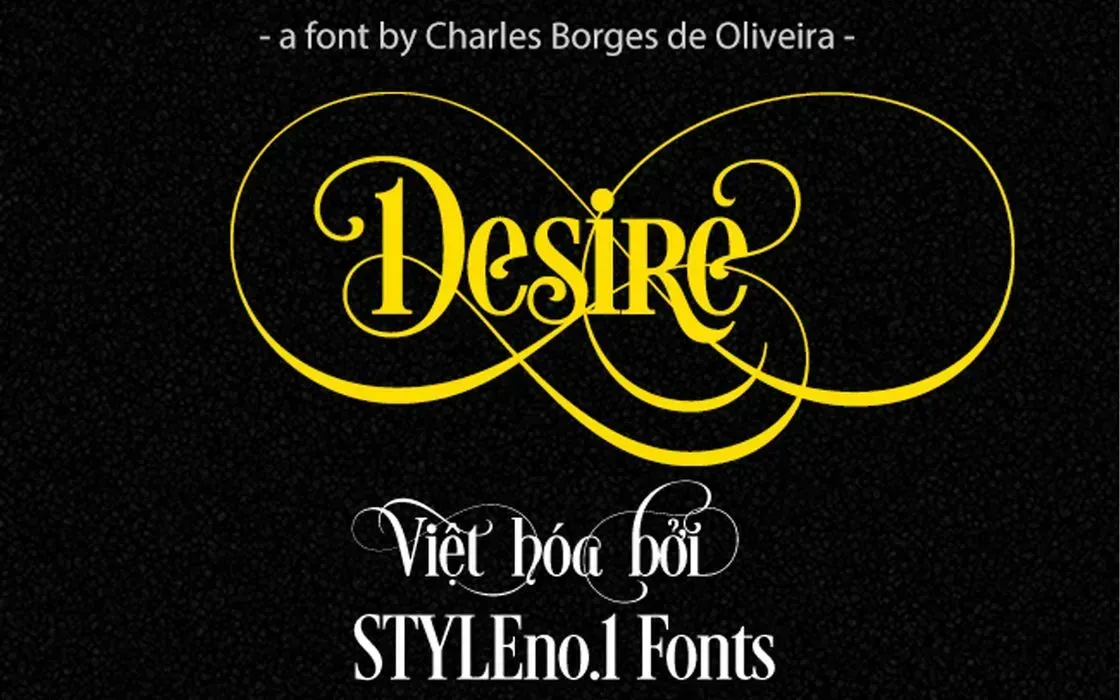
SVN Desire là một font chữ serif trang trí (decorative serif) mang phong cách quyến rũ, mềm mại và đầy tính nghệ thuật. Khác với các font serif truyền thống, Desire được thiết kế với các đường cong uyển chuyển, nét thanh – nét đậm tương phản mạnh và phần chân chữ cách điệu uốn lượn tinh xảo. Tổng thể font mang lại cảm giác sang trọng, gợi cảm và nổi bật, đặc biệt thích hợp cho những thiết kế cần gây ấn tượng ngay từ cái nhìn đầu tiên.
Font gốc Desire được thiết kế bởi Charles Borges de Oliveira – một nhà thiết kế nổi tiếng với các font chữ mang tính thẩm mỹ cao, thường xuất hiện trong thương hiệu thời trang, bìa tạp chí, bao bì cao cấp, thiệp mời, poster điện ảnh và mỹ phẩm cao cấp. Với hơn 1000 glyphs, bản gốc có hệ thống ligatures và alternates phong phú, tạo nên sự đa dạng thị giác vượt trội.
Phiên bản SVN Desire được nhóm SVN Fonts Việt hóa một cách công phu, bổ sung đầy đủ dấu tiếng Việt và vẫn giữ nguyên độ mềm mại, tinh tế của bản gốc. Font tương thích tốt với các phần mềm thiết kế như Photoshop, Illustrator, InDesign, Canva và các nền tảng trình bày cao cấp.
Nếu bạn đang tìm một font chữ có chân mềm mại, nữ tính nhưng vẫn táo bạo và đầy cuốn hút, thì SVN Desire chính là lựa chọn lý tưởng để tạo nên những thiết kế mang tính thời trang, sang trọng và nghệ thuật – nơi từng con chữ là một tuyên ngôn thẩm mỹ.